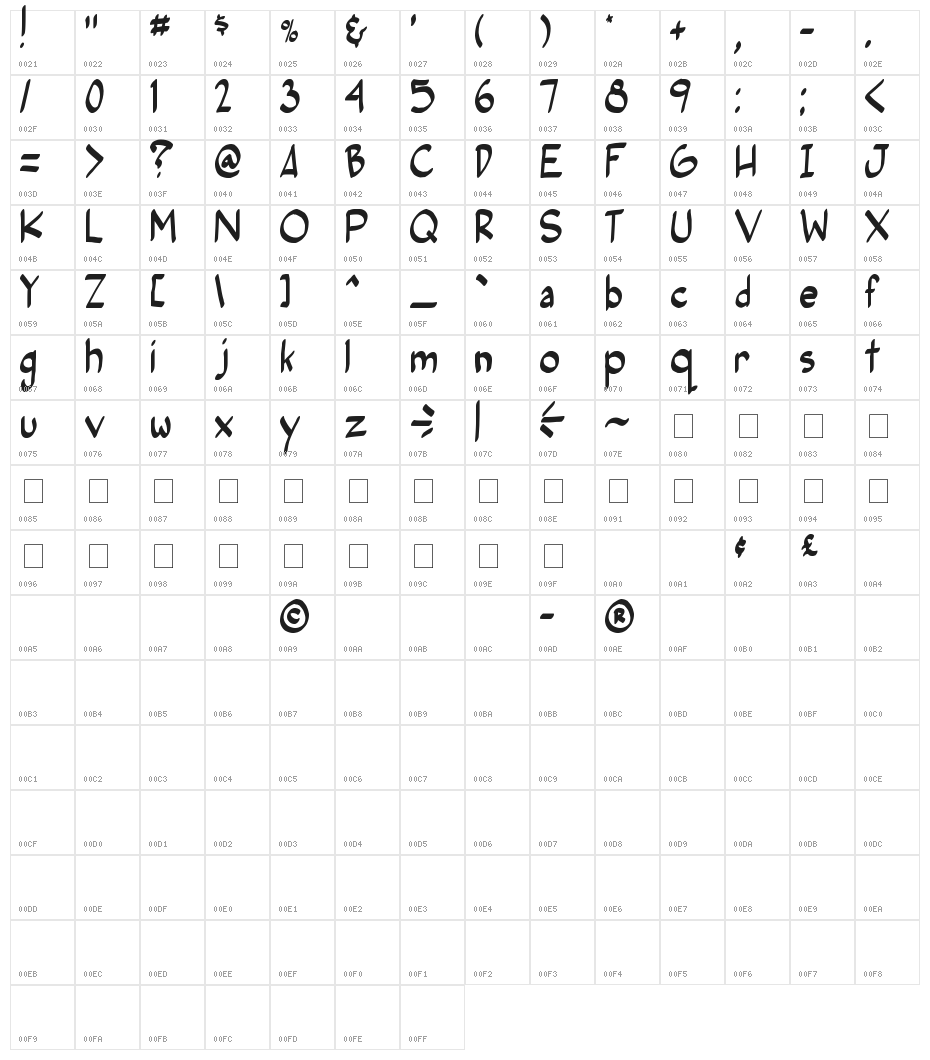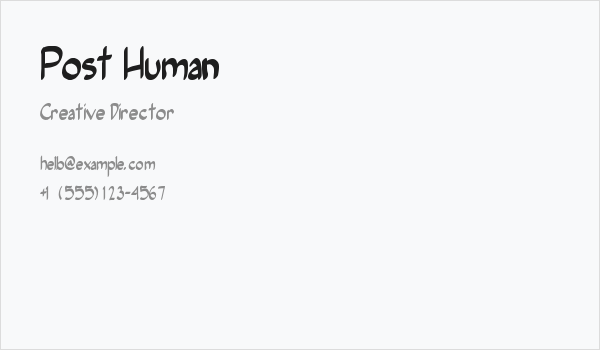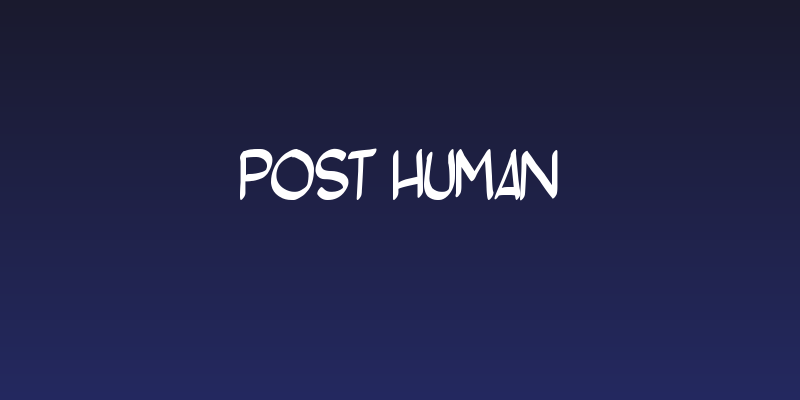
Post Human Font
| श्रेणियाँ | Comic |
| समग्र शैली | Decorative |
| उपयोग का मामला | Headlines, Logos, Posters |
| सुझाए गए प्रोजेक्ट | Ideal for creative projects such as posters, invitations, and social media graphics where a fun and energetic vibe is desired. |